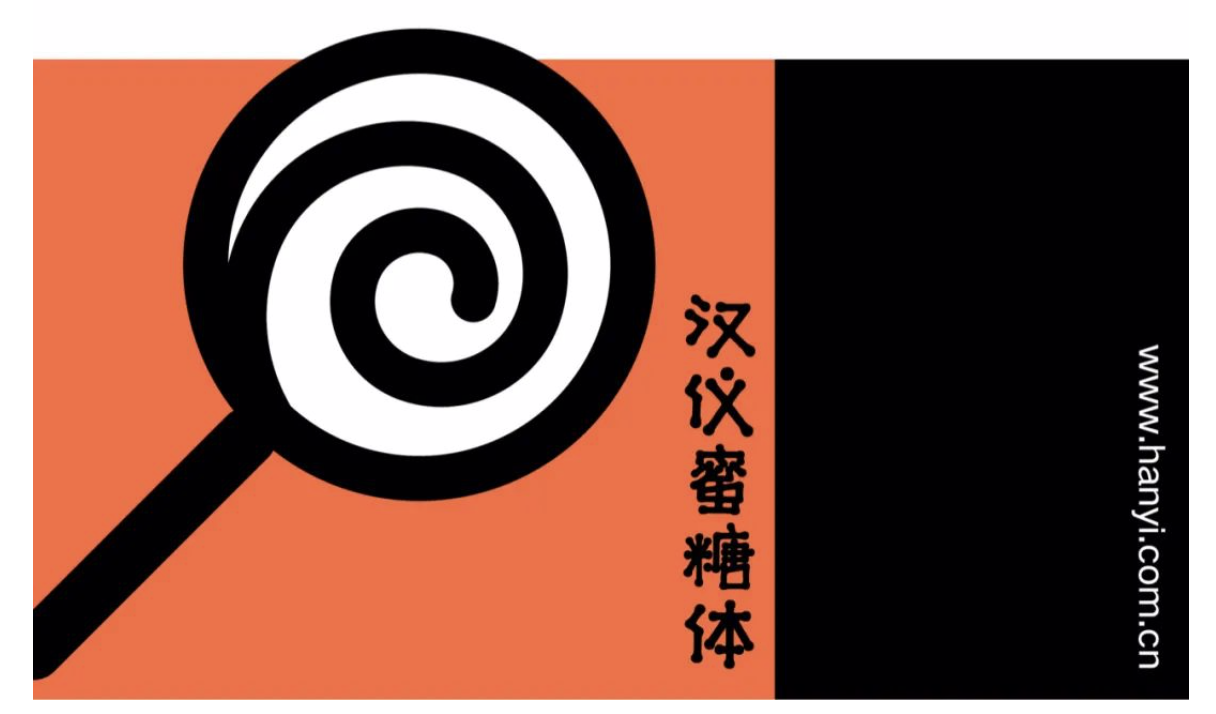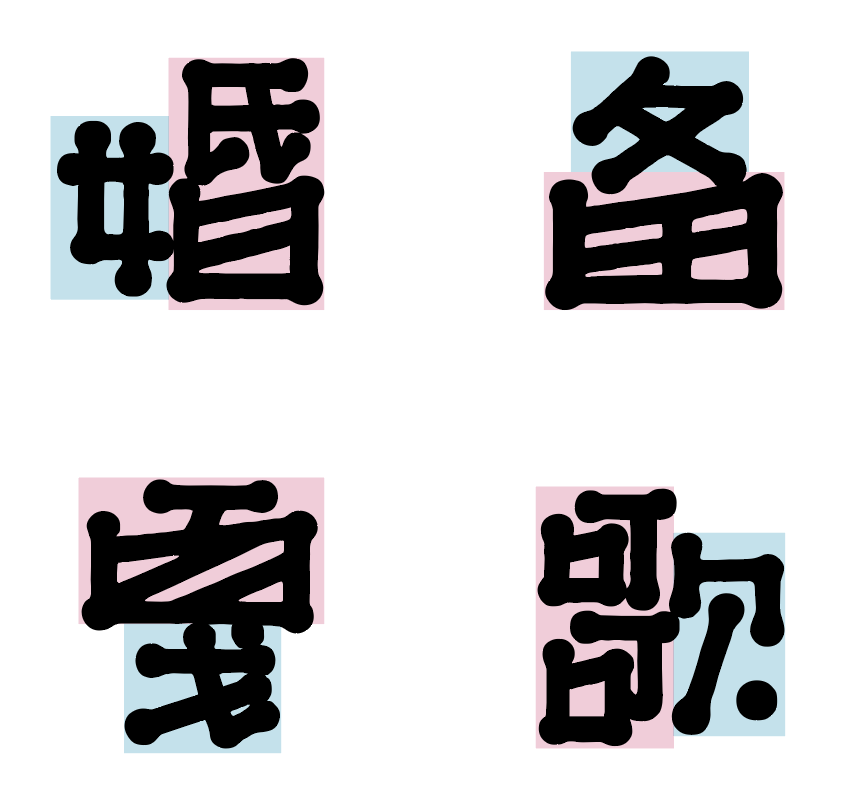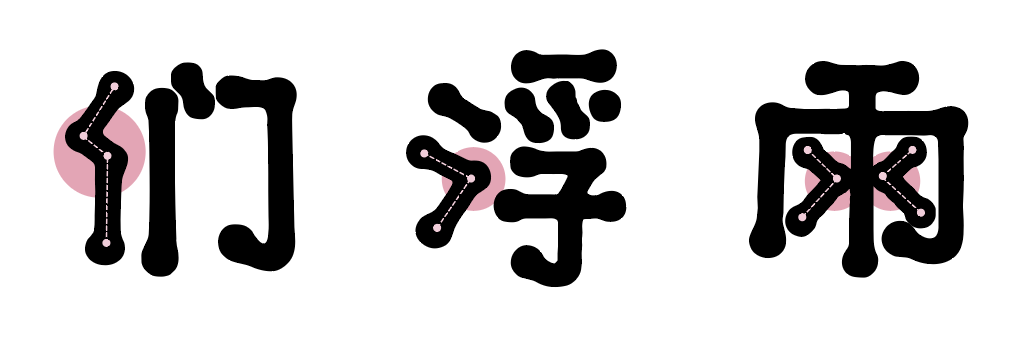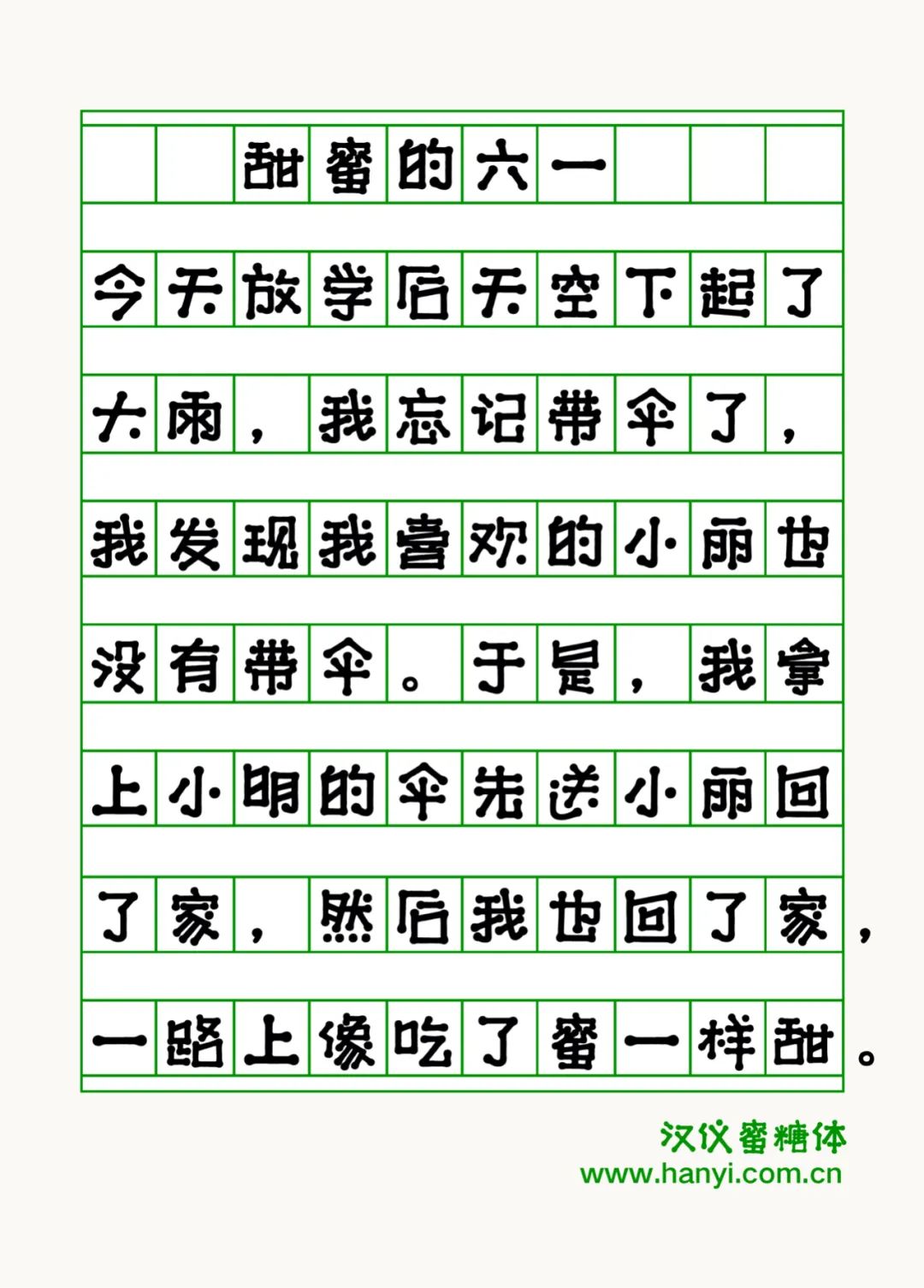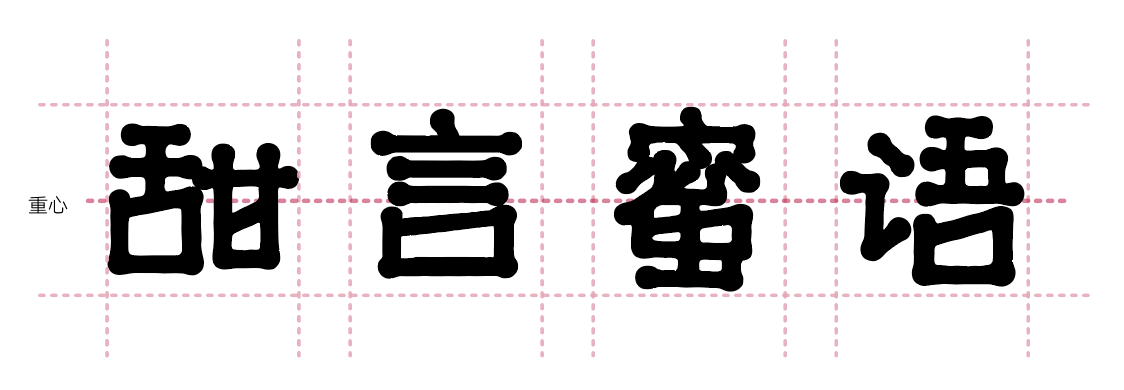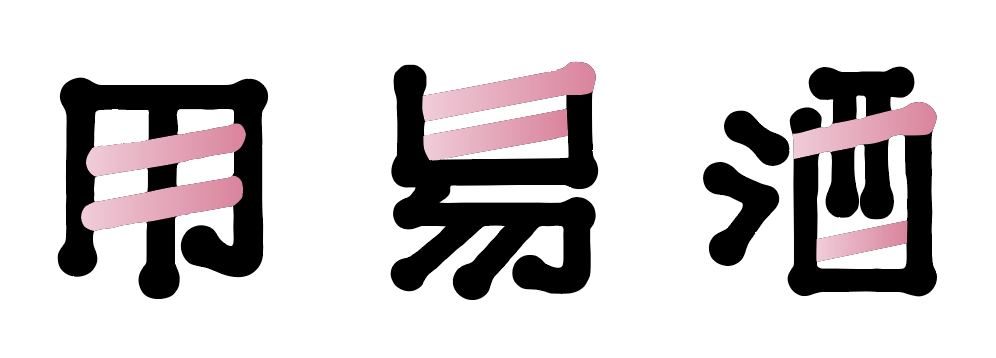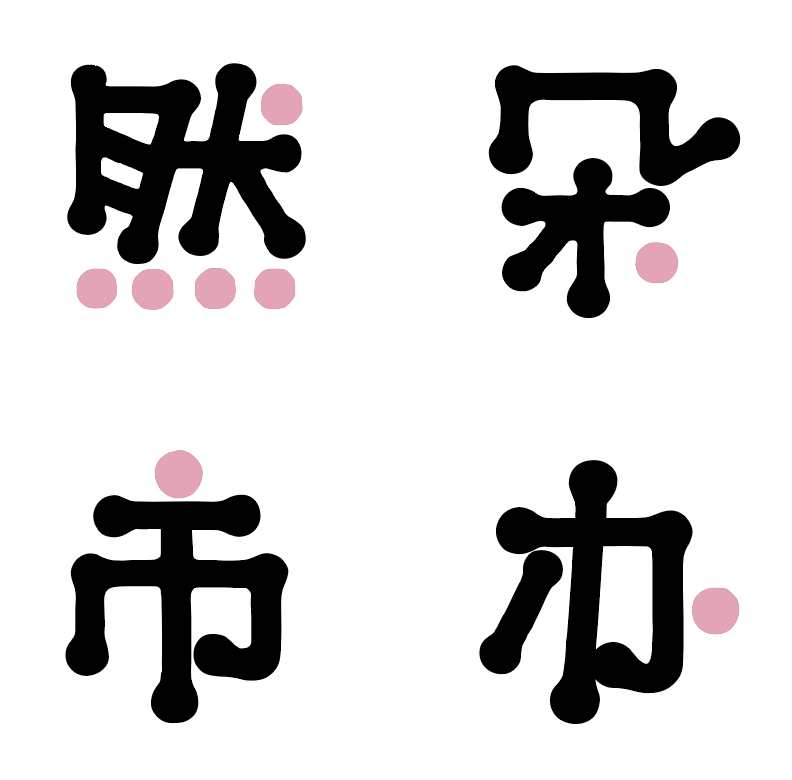
汉仪蜜糖体字体介绍,汉仪蜜糖体设计灵感
汉仪蜜糖体 | 整体特点
“汉仪蜜糖体”是一款字形生动,笔画童稚,结构新奇的创意手写字体,它的性格活泼可爱,像糖果一样给人带来甜蜜的感觉,适用于插图、漫画等轻松活泼的设计场合及领域。接下来让我们一起品尝这款蜜糖一样的字体吧~
汉仪蜜糖体 | 字形特点
“汉仪蜜糖体”的笔画简洁稚嫩、字形欢快活泼,看似写法夸张、随意,实则结体严谨、重心一致。方形的字体就像一个个糖块一样甜蜜诱人。
汉仪蜜糖体 | 结构灵活
“汉仪蜜糖体”的字体结构丰富多变,有着各式各样的大小对比关系,为字体增添了更多趣味性。
汉仪蜜糖体 | 笔画特点
“汉仪蜜糖体”的起笔收笔和转折处都有着圆润凸起的装饰,就像棒棒糖一样,细节处均体现着字体的调皮可爱。
“汉仪蜜糖体”的部分横笔画向右上倾斜,显得古灵精怪、俏皮可爱。
“汉仪蜜糖体”的点笔画用圆来表现,就像一颗颗圆滚滚的糖球,与其他笔画的两端装饰相呼应。
“汉仪蜜糖体”是作者用蘸着墨汁的木棍书写的,在书写时会有一些连笔笔画。而这种笔画之间的粘连感就像是化掉的糖果一样甜到你的心里。
汉仪蜜糖体 | 中西文匹配
“汉仪蜜糖体”的西文字母充分吸收了中文甜蜜可人、轻松活泼的性格特点,笔画两端有着相同的装饰,中西文搭配使用十分和谐。
汉仪蜜糖体 | 排版效果